Monotype LETS、モトヤLETS、イワタLETSの新書体が7月18日から提供
フォントワークスは、年間定額制フォントサービス「Monotype LETS」「モトヤLETS」「イワタLETS」の新書体を2018年7月18日(水)から提供を開始することを発表した。
Monotype LETS 2018年7月18提供新書体
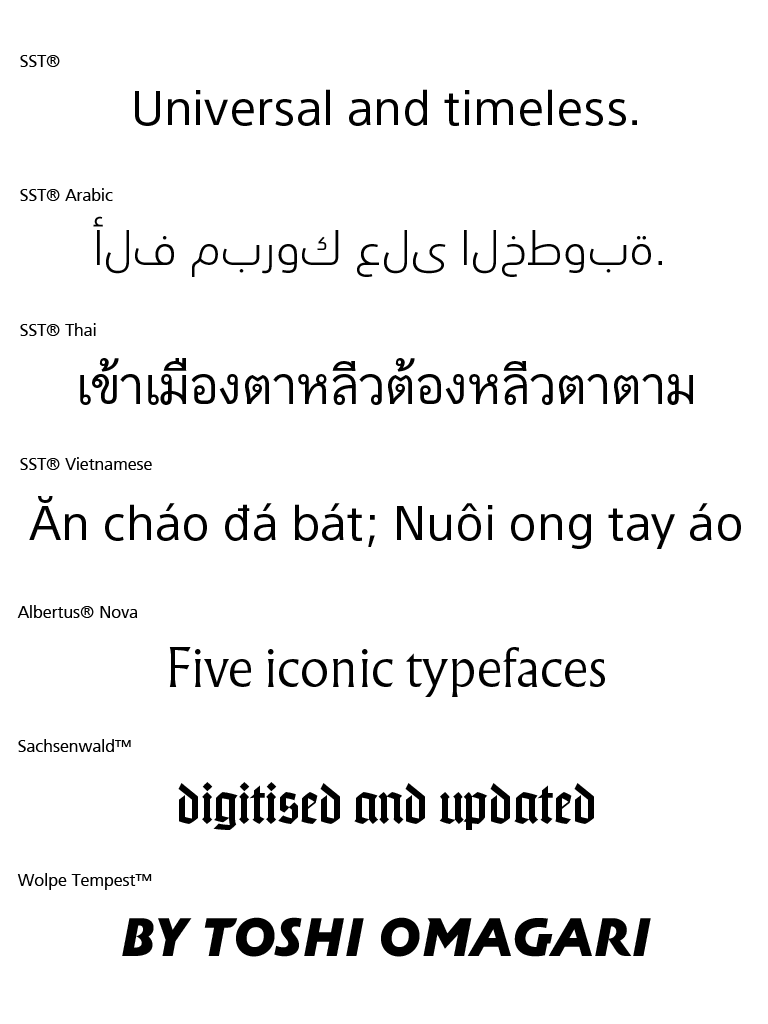
Monotype LETSにはSST®とThe Wolpe Collectionを含む圧巻の1,331書体が追加される。
SST®は、SSTは、ソニーとMonotype社が共同で開発したソニーのグローバル・ブランディングと93言語のサポートを目的として開発されたソニーのコーポレートフォント。Monotype社タイプディレクター小林章氏のディレクションにより開発が進められた。今回、SSTRの欧文書体および多言語書体が利用できるようになる。
また、4月に追加されたWolpe Pegasus™、Wolpe Fanfare™に加え、「The Wolpe Collection」を構成する AlbertusR Nova、Sachsenwald?、Wolpe Tempest? も追加される。
Monotype Studioの大曲都市氏によって、1930年代のBerthold Wolpeのデザインを現代に合わせて拡張し復活した「The Wolpe Collection」が加わる事になる。
その他、既にMonotype LETSで提供済みの書体に関しても、より多くのウェイトや文字セットのバリエーションが加わった。
モトヤ LETS 2018年7月18提供新書体
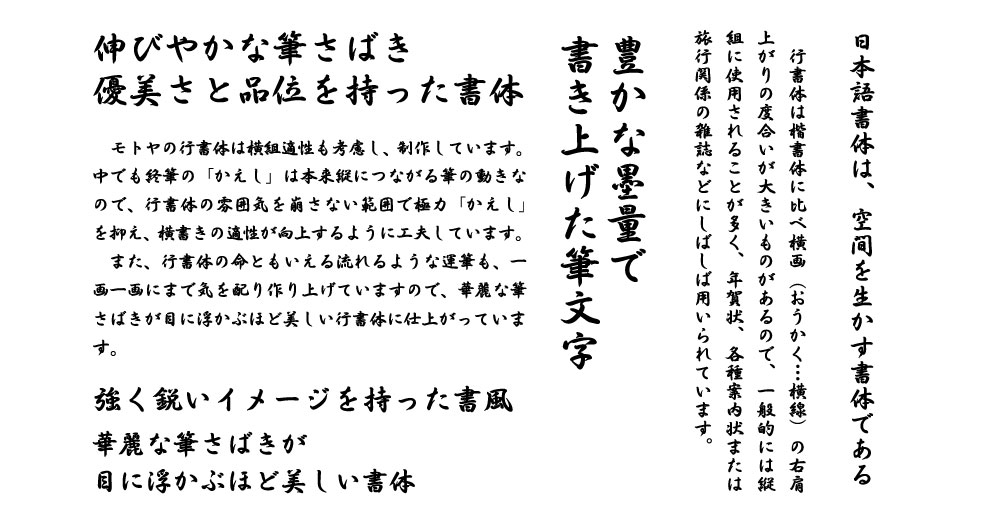
モトヤ LETS新書体として、伝統書体に伸びやかな筆さばきで優美さと品位を持った行書体「Sモトヤ行書 Std W5」が加わる。
Sモトヤ行書 W5[Std]
イワタ LETS 2018新書体
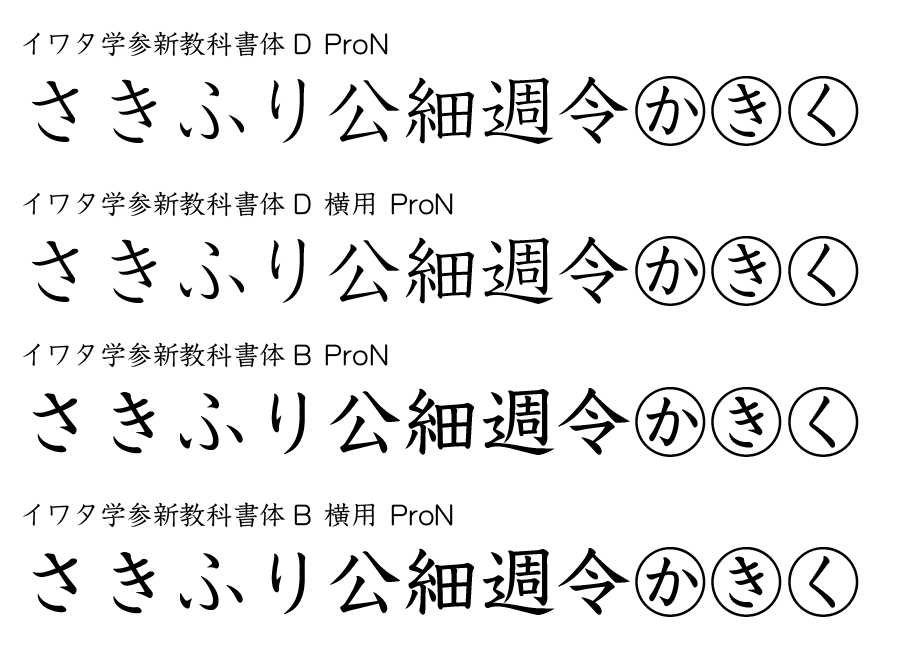
イワタ LETS 2018新書体として、現代に合わせ新しい教科書体としてデザインされた「学参新教科書体」ファミリーの4書体が追加される。
「イワタ学参新教科書体」の横用は、横組みにした際にかなの高さが揃うよう設計されており、漢字や英数字が混ざってもばらつかないデザインになっている。
イワタ学参新教科書体D ProN
イワタ学参新教科書体D 横用 ProN
イワタ学参新教科書体B ProN
イワタ学参新教科書体B 横用 ProN